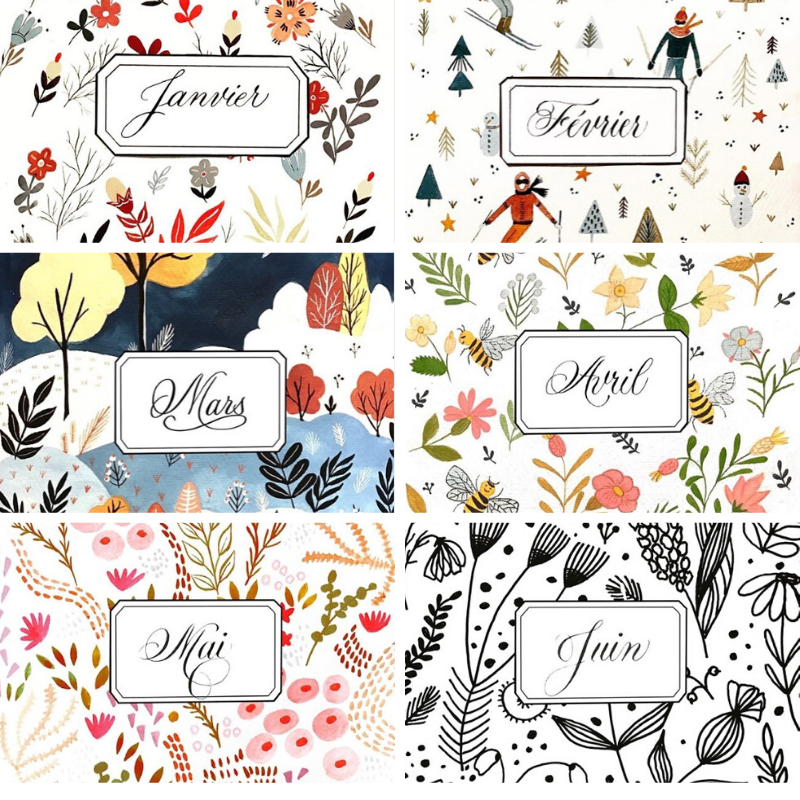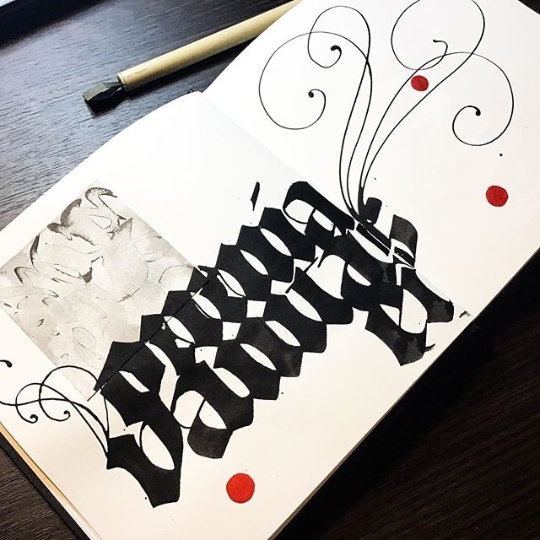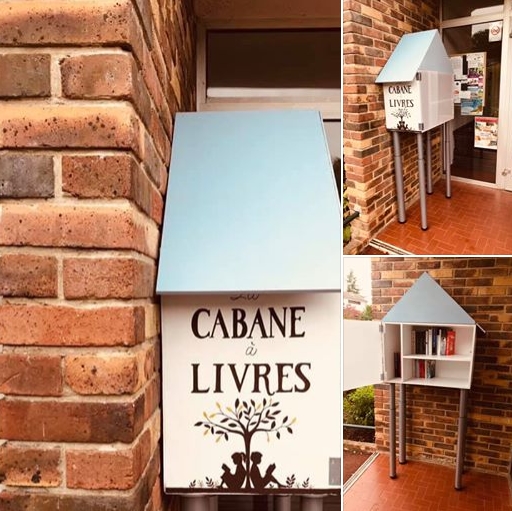
Comme chaque année je partage un petit bilan et une liste d’envies pour la nouvelle année qui commence. Quand je pense à l’année 2019 j’ai bêtement l’impression de n’avoir pas fait grand chose. Je dis bêtement, car en y réfléchissant de plus près, ce n’est pas du tout le cas. Ce sentiment est certainement dû au fait que cette année je me suis plus écoutée et j’ai laissé tombé plein de choses en cours de route : par manque de temps, par lassitude, par manque d’intérêt. D’où cette impression d’inachevé… Cela dit, j’ai quand même fait un petit tour dans ma mémoire ce qui m’a permis de voir qu’un bout de chemin avait été parcouru, et que sur ce chemin, il y a eu de très belles choses.
Les projets inachevés
Dans les projets inachevés, il y a eu le Matsbootcamp, le fameux « camp d’entrainement » à l’illustration animé par l’agent américaine Lilla Rogers. Je n’ai pas été transportée par les sujets (sauf un sur l’exploration des textures), et je n’étais pas du tout dans l’état d’esprit « challenger ». A vrai dire ça m’a même carrément saoulée, le côté starting-block dès qu’on a les sujets, les participantes qui postent des trucs supers léchés une heure après et qui s’auto-congratulent… un peu plombant, et je n’étais pas la seule à ressentir la même chose. Donc je ne suis pas allée au bout, et du coup, pas de bootcamp en 2020.
J’ai aussi participé un peu à l’arrache à « #36daysoftype » (un challenge sur Instagram, où on poste une lettre par jour puis 10 chiffres), que j’ai laissé tombé à la lettre N. Pareil, ça m’a agacée de voir tout ce qui tombait chaque jour, franchement, la majorité des gens doivent le préparer d’une année sur l’autre ce qui tue la spontanéité du truc.
Ensuite, j’avais démarré une petit compo pour chaque premier jour du mois, que j’ai laissé tomber en juin, par manque de temps.
Pas glop tout ça, très mauvais pour l’ego de ne pas finir ce qu’on a commencé, mais j’assume. Faire des choix et savoir dire non, ça fait partie du chemin, non ? A cet égard, je crois que je ne vais faire aucun challenge en 2020 (du moins à cette heure, ce n’est pas du tout mon état d’esprit !).
… Mais aussi une année de belles explorations !
Tout n’est pas noir, heureusement et 2019 a aussi généré de belles surprises et de bons moments :
• Deux stages de Chancelière très différents et très enrichissants : l’un avec Massimo Pollelo, l’autre avec Yves Leterme. Il me reste beaucoup de travail pour parvenir à un niveau convenable, mais je pense avoir eu de bons déclics.
• Un super stage autour de la Textura avec Vincent Geneslay chez Barbedor qui m’a donné envie de me re-pencher sur les écritures gothiques.
• La réalisation d’une boite à livre avec un voisin, petit chantier qui a été bien accueilli dans mon quartier à la rentrée
• Un cours en ligne avec l’illustrateur espagnol Adolfo Serra (sur Domestika) qui m’a donné une inspiration d’enfer et m’a poussée à travailler davantage dans des carnets, à re-explorer les mediums et les textures, à faire beaucoup de recherches personnelles. En outre, j’ai pu (re)découvrir les monotypes avec un œil différent et me décomplexer par rapport à mon côté parfois brouillon et compulsif en travaillant différemment.
• J’ai aussi refait le challenge #folktaleweek pour le fun au mois de novembre et participé à un collectif qui s’appelle #portfolioclub sur Instagram dans lequel on nous propose un sujet de création par mois (ce qui est amplement suffisant !).
#Folktaleweek 2019
La cabane à livre : petite bibliothèque de quartier pour le dépôt/prêt de livres
En gros, le déclic cette année a été de faire des choix, de me recentrer sur ce que j’aime vraiment faire et d’arrêter de courir partout. Ça a l’air de rien, mais ces dernières années j’ai exploré beaucoup de techniques et de styles, j’ai bavé devant le travail de nombreux artistes, j’ai voulu faire pareil, et maintenant je sais dire « non, c’est chouette mais ce n’est pas pour moi ». J’ai aussi apprécié de me couper un peu des réseaux sociaux et de travailler seule dans ma bulle et dans mes carnets.
Les envies 2020
Ma plus grosse envie pour 2020 est de continuer à rêvasser, de faire avec ce que j’ai (je m’engage à réduire mon budget beaux-arts tant qu’une étagère de ma bibliothèque ne s’est pas totalement vidée), et surtout de ne faire QUE ce que j’aime.
Plus précisément, j’ai envie de travailler les grosses lettres, de tailler dans le gras, de titiller les capitales (toutes sauf la Romaine, trop dur, ce n’est pas pour moi, voir plus haut). Donc cela va tourner autour de la Textura Bold, de la cursive romaine, des lettres façon David Jones. Je n’exclue pas pour autant de retravailler ma Chancelière pour l’amener au niveau supérieur, et de faire un petit détour vers la Ronde qui me fait de l’œil ces derniers temps.
Il y aura toujours des fleurs, des oiseaux, des feuillages, de la poésie, sans doute avec un peu plus de graphismes et de textures.